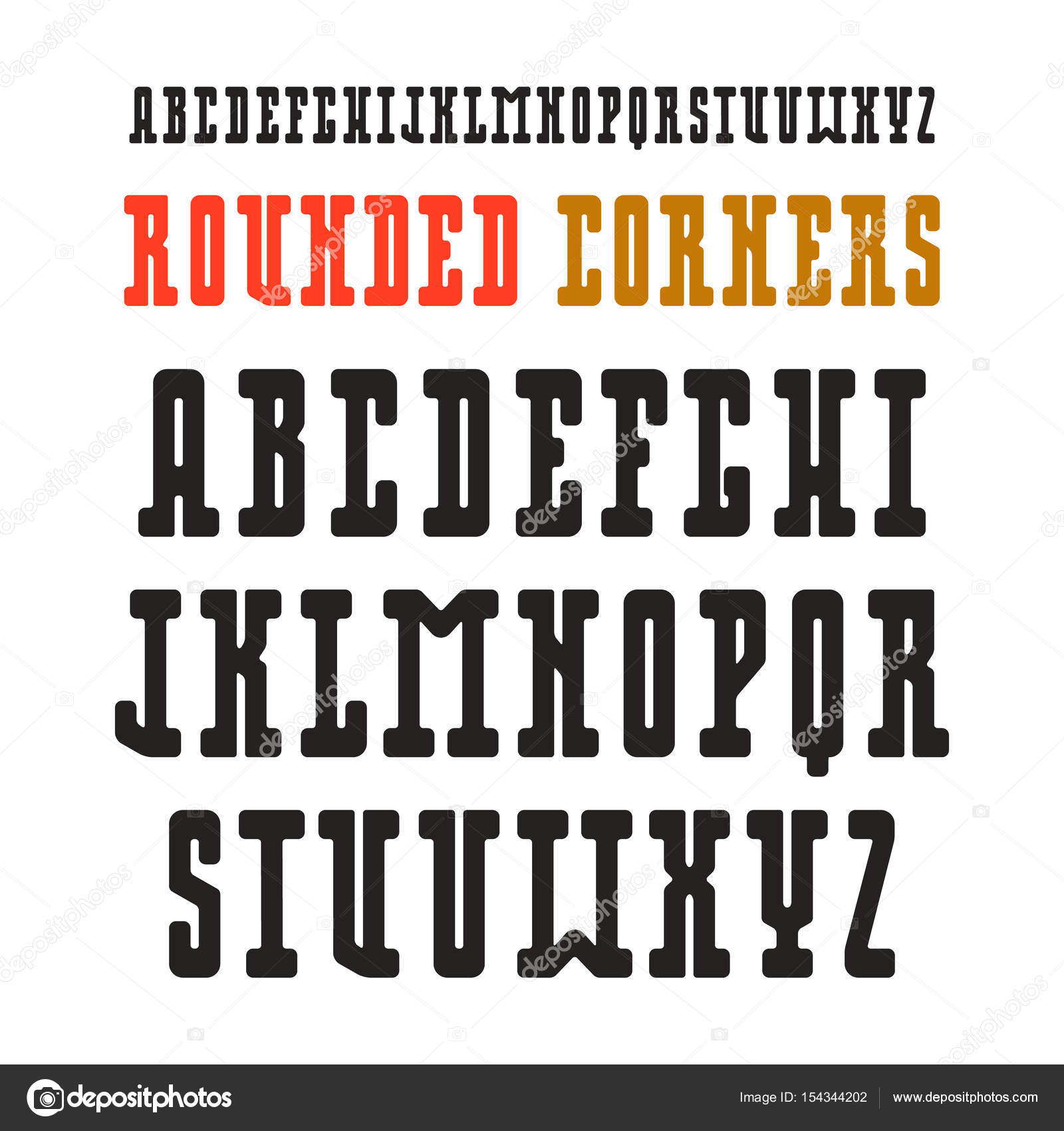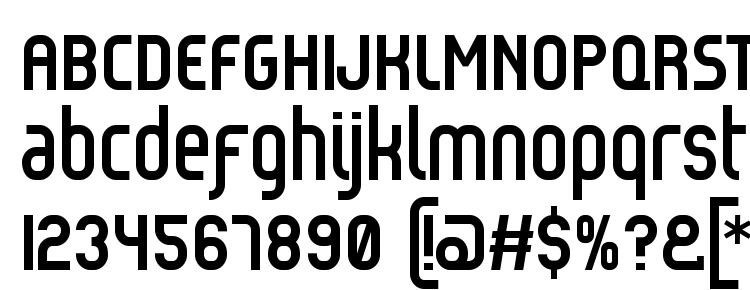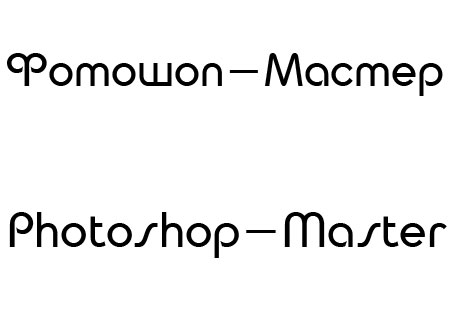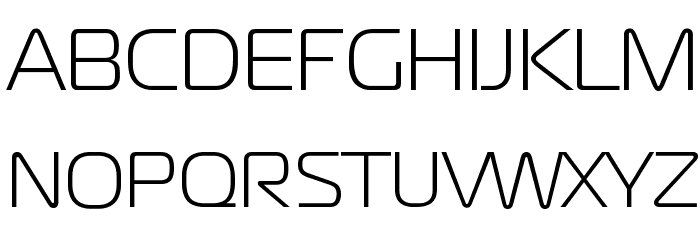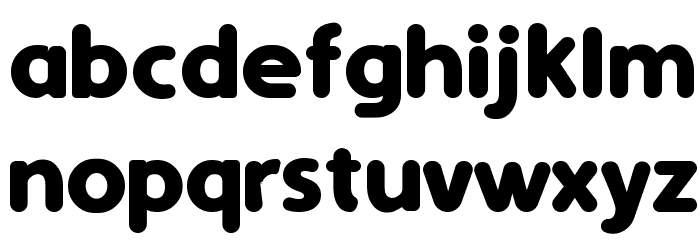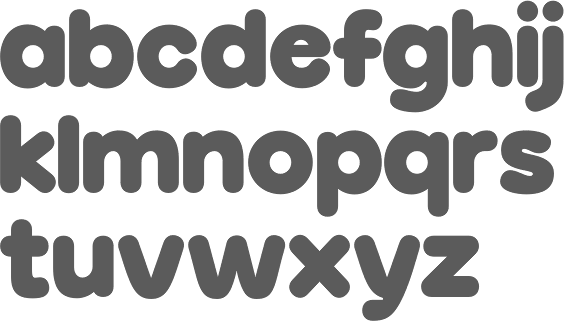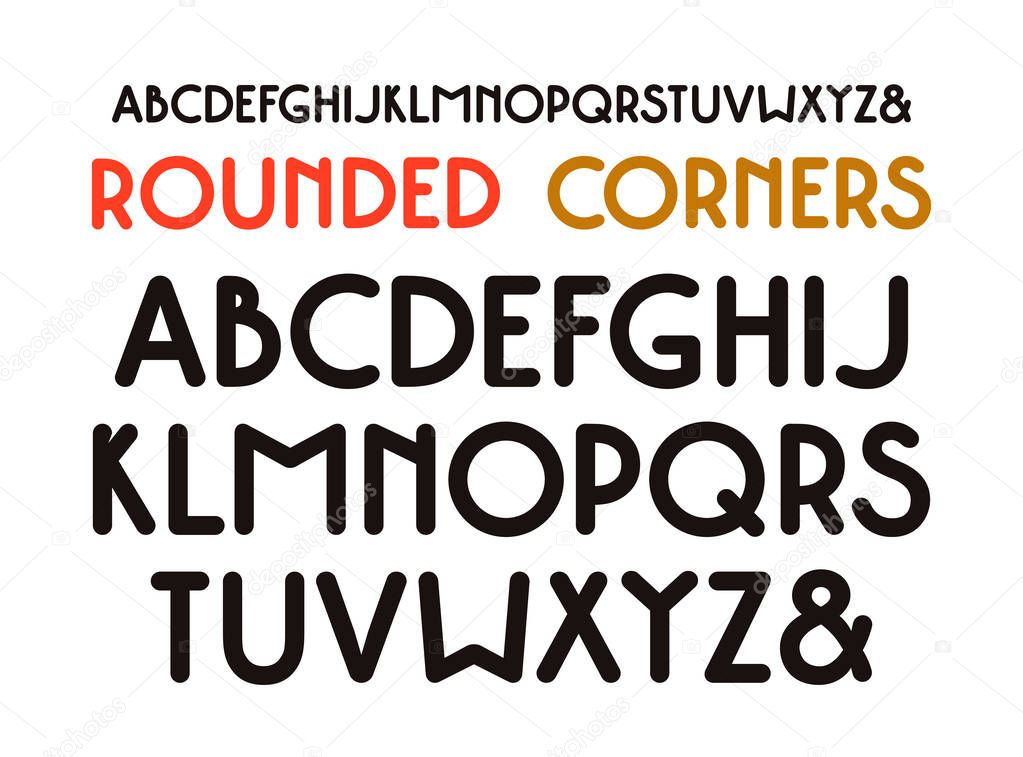
Шрифт скругленный русский: Круглые, округлые шрифты — каталог русских бесплатных шрифтов. Скачать на Facefont
Молодежный шрифт
Акцидентный гротеск
Уверенный рукописный шрифт
Яркий акцидентный шрифт
Текстовая антиква
Кириллица в Google Fonts: неогротески
Сегодня бесплатный шрифт не обязательно означает плохой. Увы, в кириллической части тут всё ещё минное поле, но есть и хорошие новости. Наша критика и наши советы не призваны стать истиной в последней инстанции: это лишь экспертная оценка трёх специалистов, находящихся в одной системе ценностей. К тому же всегда стоит помнить, что в дизайне нет запрещённых приёмов. В руках смелого, уверенного типографа любой баг может превратиться в фичу, но, прежде чем рисковать, нужно точно разобраться, что является багом.